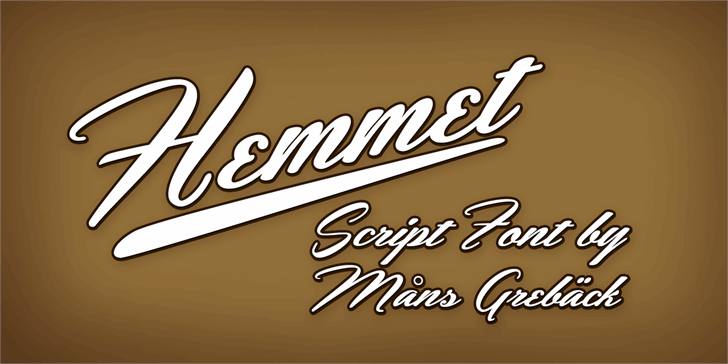
A Hemmet é uma fonte script que oferece um toque suave e elegante para suas criações digitais. Desenvolvida pelo designer Hamilton, esta fonte traz ao seu design uma delicadeza característica de letra a mão. Suas linhas fluidas e sutis criam um visual amigável e versátil, perfeito para textos em sites, cartões de visita ou qualquer projeto que exige uma aparição sofisticada. A Hemmet não apenas oferece variedades legíveis e manejáveis, mas também adere bem às cores e ícones da sua plataforma para garantir um design harmônico. Para quem deseja explorar a vasta gama de opções disponíveis, Hamilton disponibilizou esta fonte através do site www.mansgreback.com/hemmet. Descubra por si mesmo o encanto dessa fonte elegante e única.